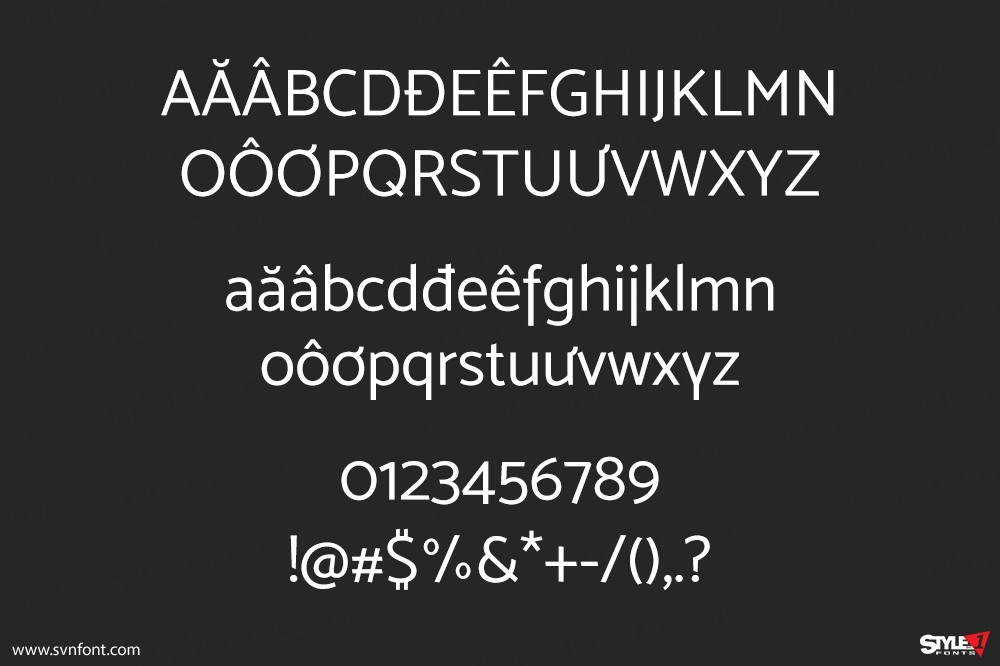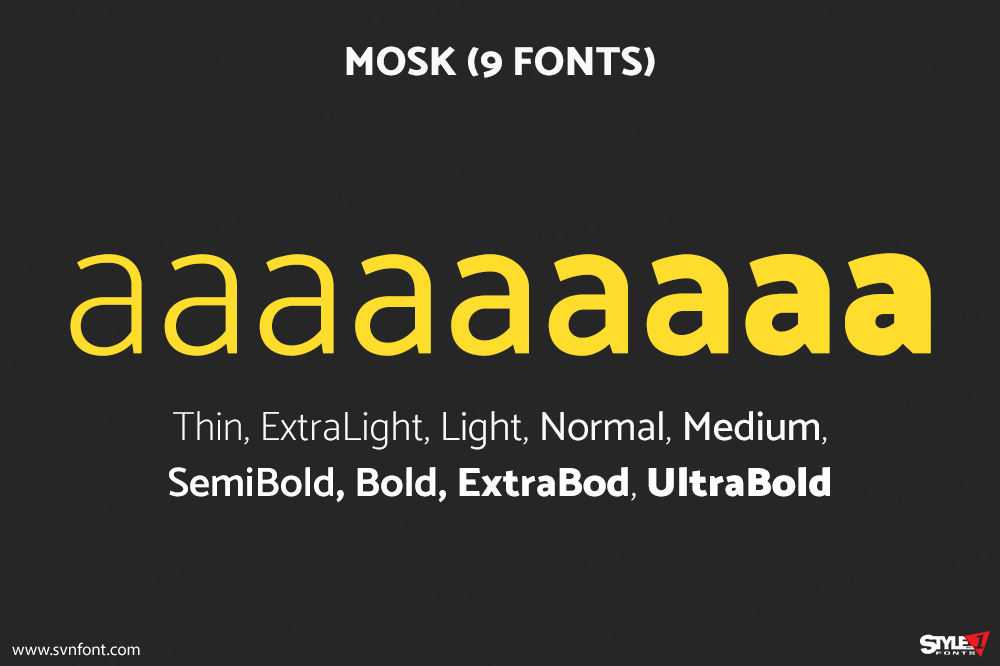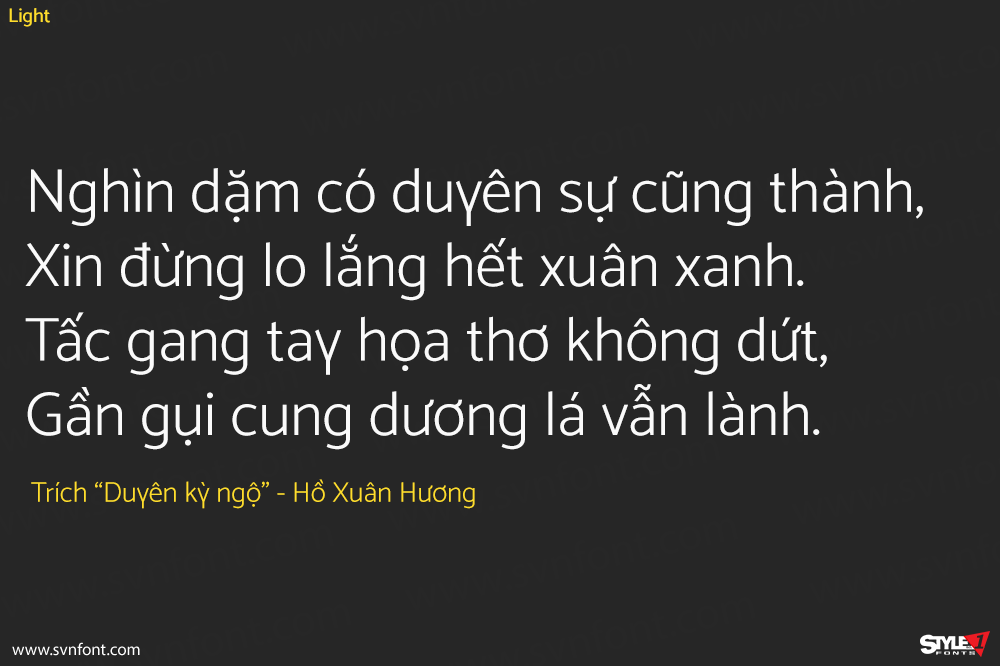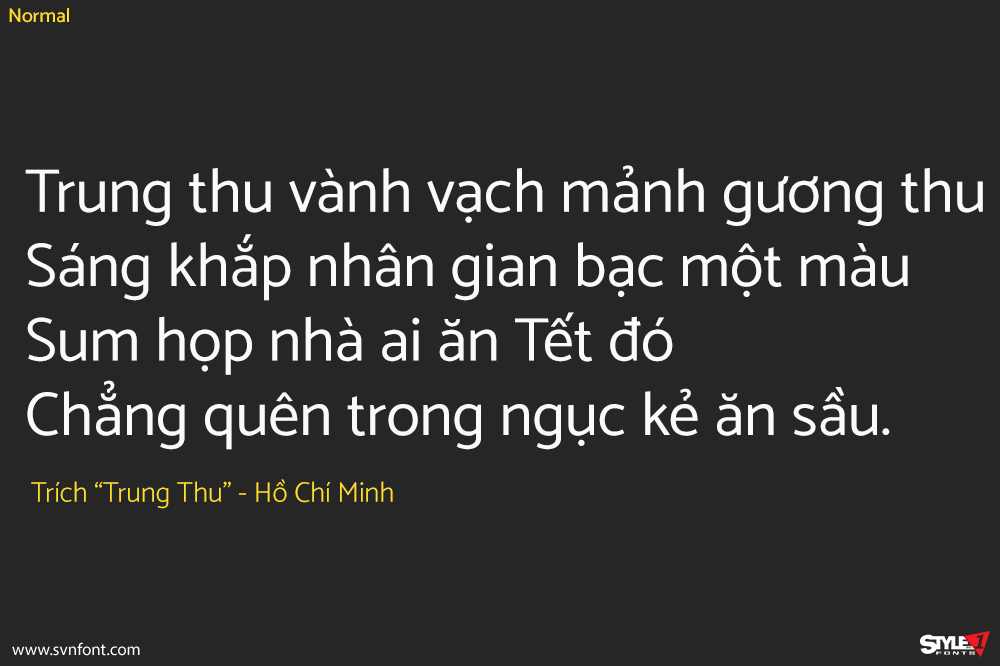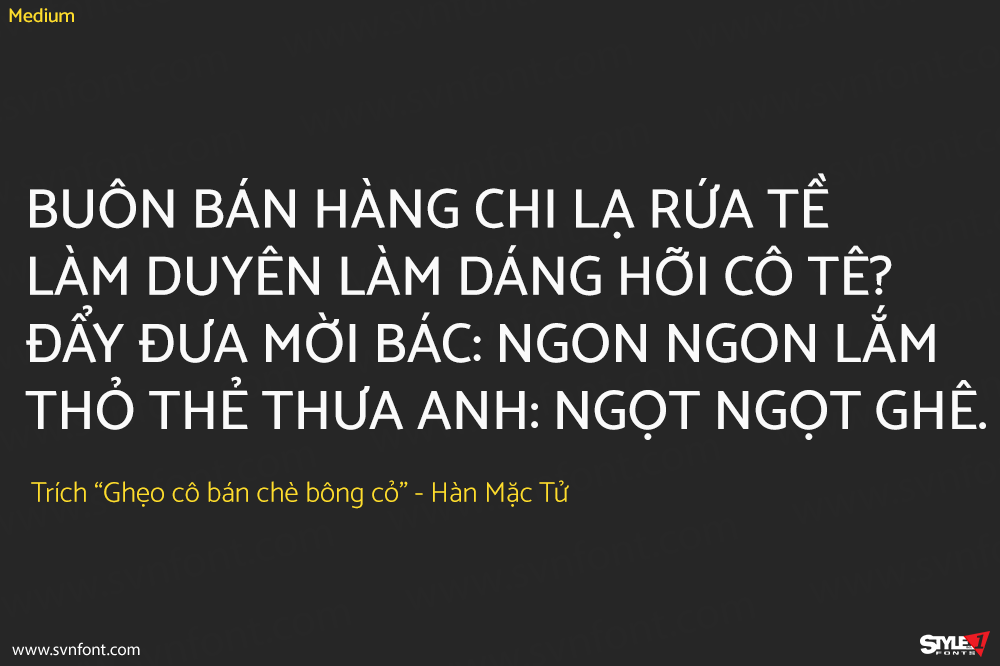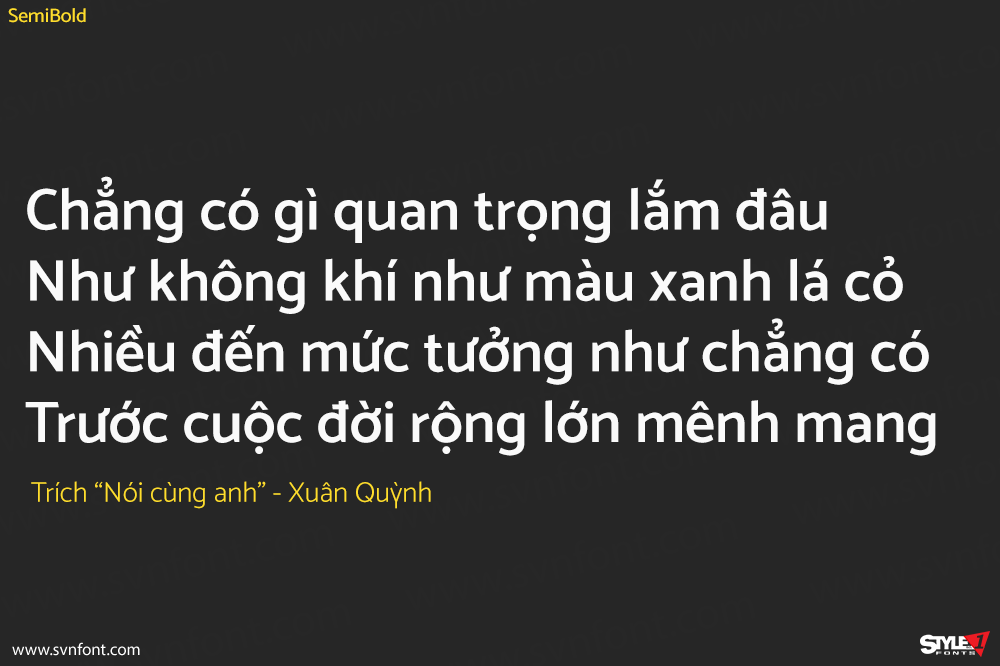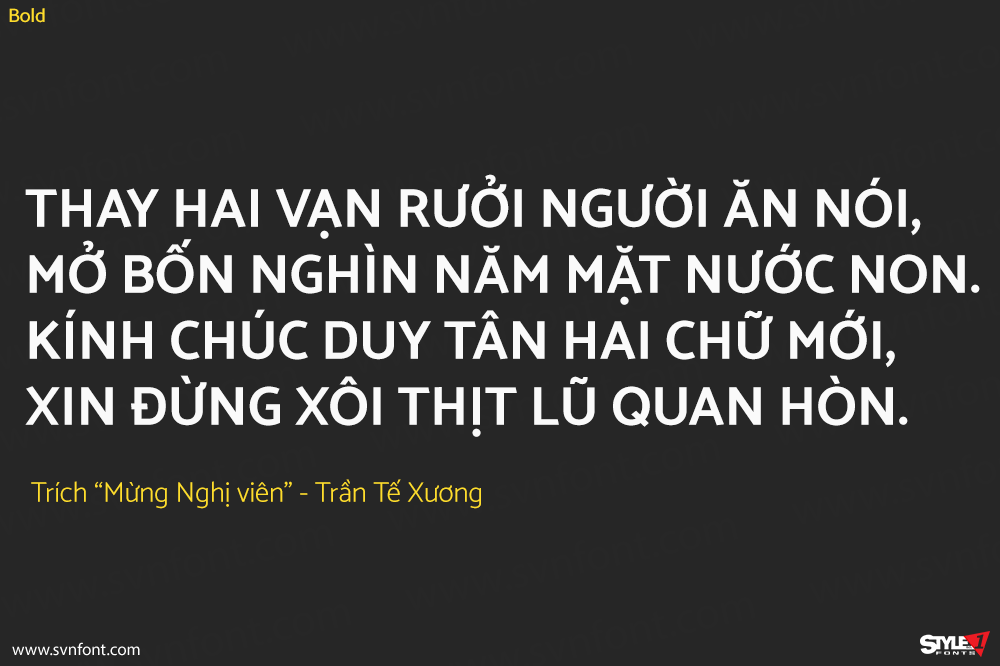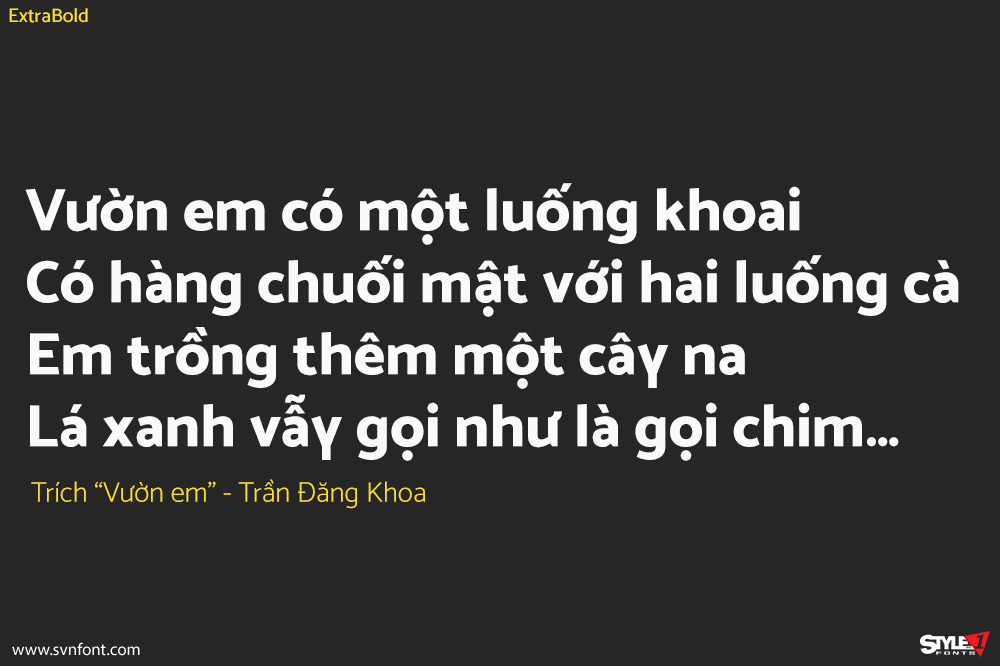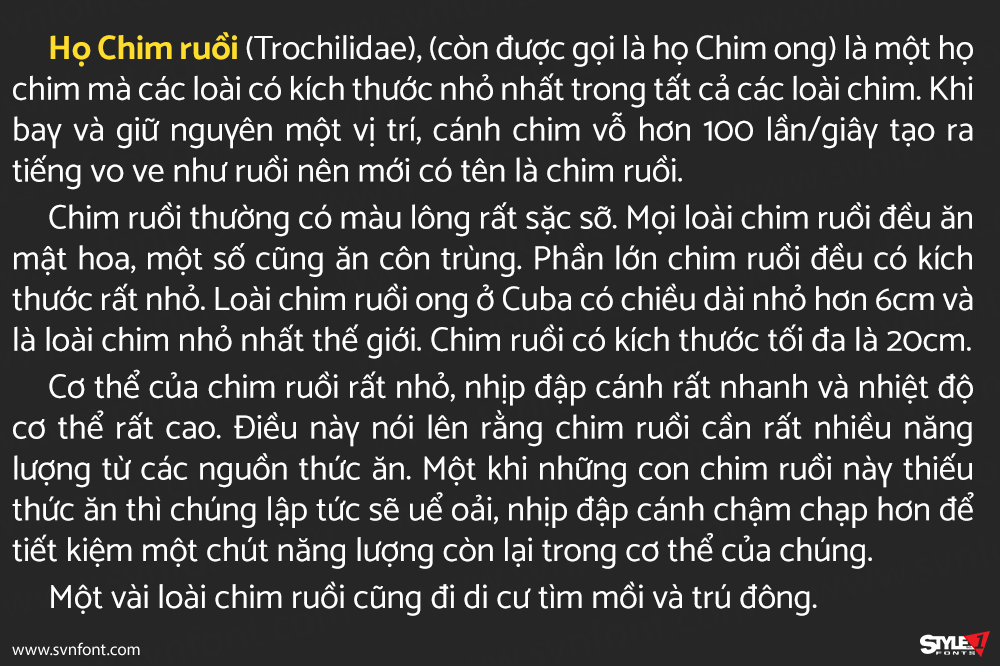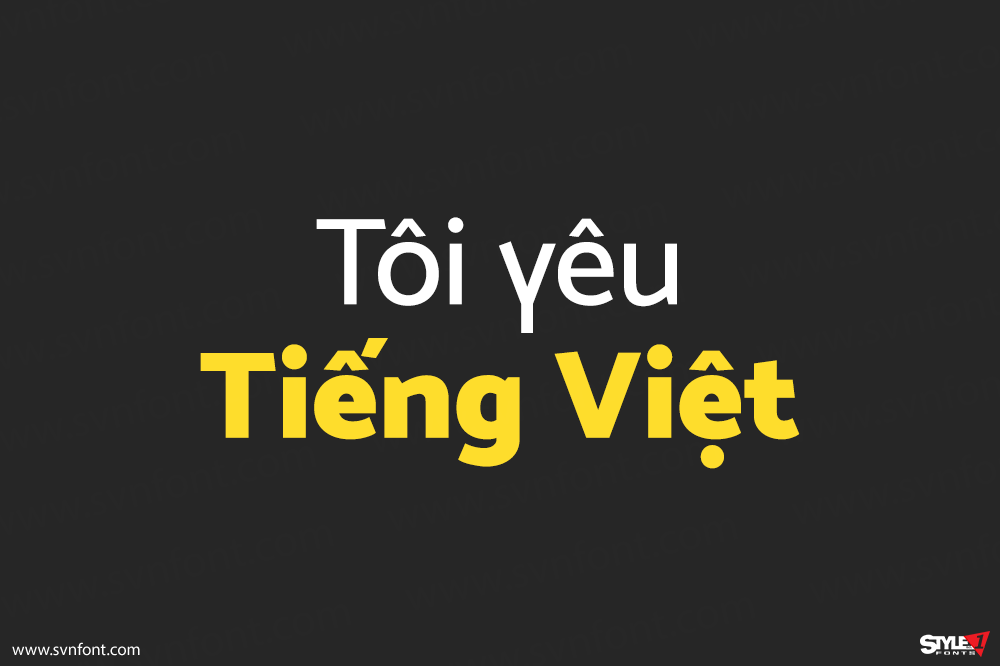
[Việt hóa] SVN-Mosk (9 fonts)
Mosk is a typeface family that consist of lowercase letters and edited versions in the uppercase version, for your logos and designs.
Nhà thiết kế: Iulian Maftei